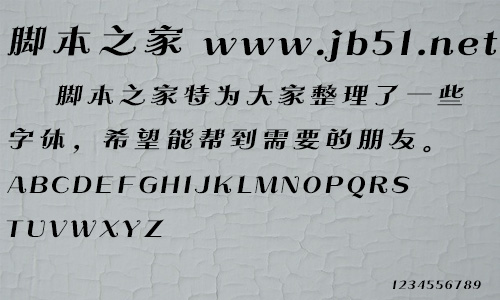
方正瑪麗體由方正字庫出品的一款不錯的藝術(shù)字體,該系列共八款字體,字體呈現(xiàn)傾斜排列,從女性漫畫風(fēng)格提取靈感,用纖細(xì)優(yōu)美的線條加上連綴的珠點,表達(dá)秀雅的情調(diào)和魅力,適合應(yīng)用于藝術(shù)設(shè)計、平面宣傳設(shè)計、網(wǎng)頁設(shè)計,書法等領(lǐng)域。
翻開七十年代少女漫畫,華麗夢幻的畫風(fēng)深受女性讀者喜愛。方正瑪麗體從女性漫畫風(fēng)格提取靈感,用纖細(xì)優(yōu)美的線條加上連綴的珠點,表達(dá)秀雅的情調(diào)和魅力。
方正瑪麗體系列包含8種不同粗細(xì)字體,適合女性纖體,健身,體育品牌,舞蹈用品,珠寶行業(yè),化妝品等商業(yè)宣傳和包裝設(shè)計。